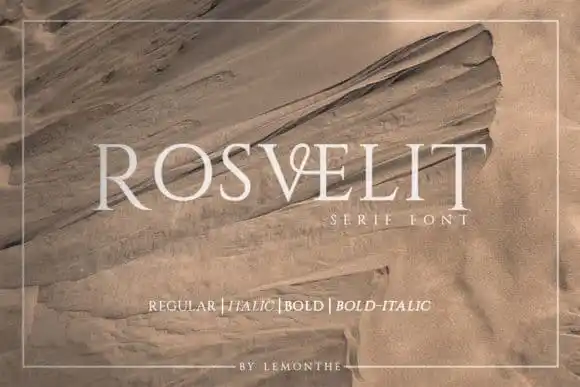
Rosvelit Serif Font
A Rosvelit Serif Font é uma escolha perfeita para designers que valorizam a elegância clássica combinada com um ritmo moderno na tipografia. Seu design de serif faz dela uma opção versátil e simples, capaz de se adaptar a uma grande variedade de projetos gráficos sem perder sua elegância intrínseca. As linhas sutis da Rosvelit não apenas enriquecem o texto em suas obras, mas também os tornam instantaneamente mais marcantes e distintivos. Se procura um recurso visual que ofereça tanto sofisticação quanto uma personalidade contemporânea, a Rosvelit é definitivamente a escolha certa. Seu designer, Lemonthe, criou este font para dar voz à sua creatividade de forma lisonjeira, tornando-as tão únicas e distintivas quanto seus projetos. Em um mundo de tipografias que variam em estilos e nuances, a Rosvelit se destaca como uma opção elegante e versátil para qualquer trabalho de design.